Tipografía en 3D: tutoriales y ejemplos
Al principio del año comenté en un artículo con una selección de el artículo
70 maravillosas tipografía en 3D para inspirarte, que aunque se puede crear obras de arte sin tipografía, resulta
difícil expresar una idea sin utilizar el texto, pues tenemos que imaginar y hacer suposiciones sobre lo que su autor nos quiere transmitir. Pero al emplear la tipografía (texto), la idea mejora pues nos aseguramos que el que la contempla pueda recibir el mensaje que esa obra o diseño quiere transmitir, por lo que la idea se transmite perfectamente.
El diseño en donde la tipografía tiene un papel destacado, requiere un gran esfuerzo de parte de los diseñadores, para mejorar y sobresalir. La familiarización con el diseño de la tipografía, a un nivel alto requiere mucho tiempo y puede ser complicado y difícil. El dominio en el empleo del
tipo de letra adecuado, los
colores, el
estilo, las
palabras clave y la
ubicación, son todos los factores cruciales para dar forma a un gran diseño con tipografía.
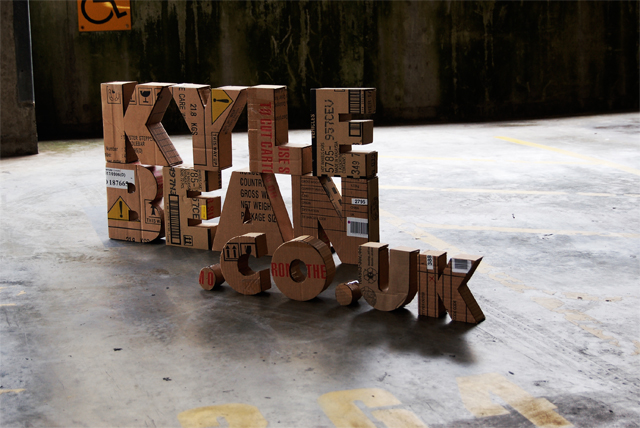
Por eso me ha llamado la atención
A Showcase of 3D Typography: Tutorials & Examples, de
myInkBlog, que nos deja un escaparate de tipografías en 3D con buenos tutoriales y algunos ejemplos.
Ya que la tercera dimensión puede ser una excelente manera de añadir carácter y estilo a los diseños donde predomina la tipografía., pues es un elemento muy importante del diseño. En dicho artículo encontraremos diferentes tutoriales que te enseñarán a realizar una variedad de efectos 3D tipográficos para incorporar en su trabajo. Luego nos muestra algunos bellos ejemplos de tipografía en 3D para inspirarte y poner en práctica las recién aprendidas técnicas. Por lo tanto, estruja tu cerebro, y saca a relucir tu inspiración, y explora el mundo de las tres dimensiones.